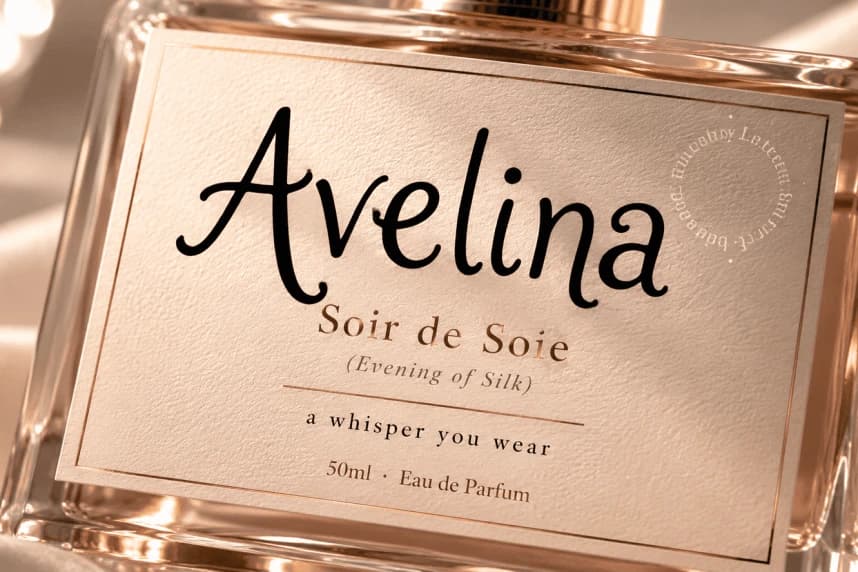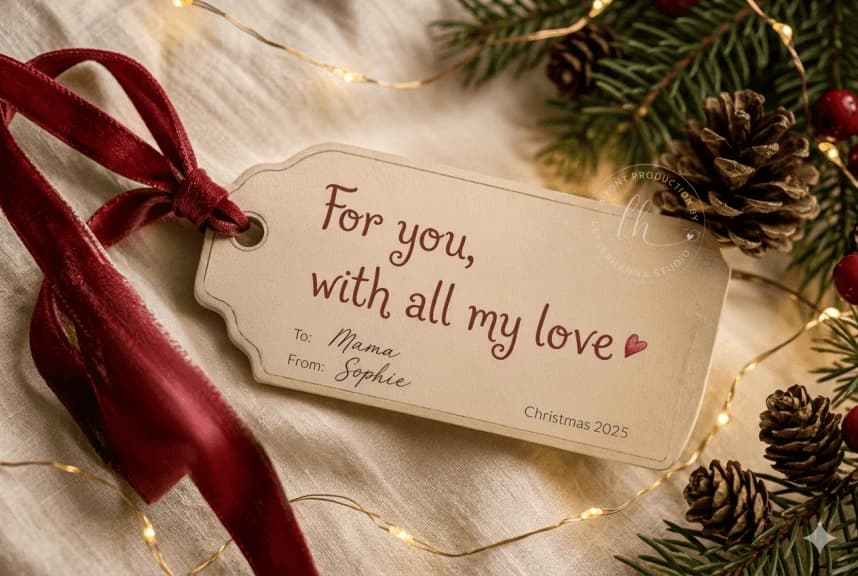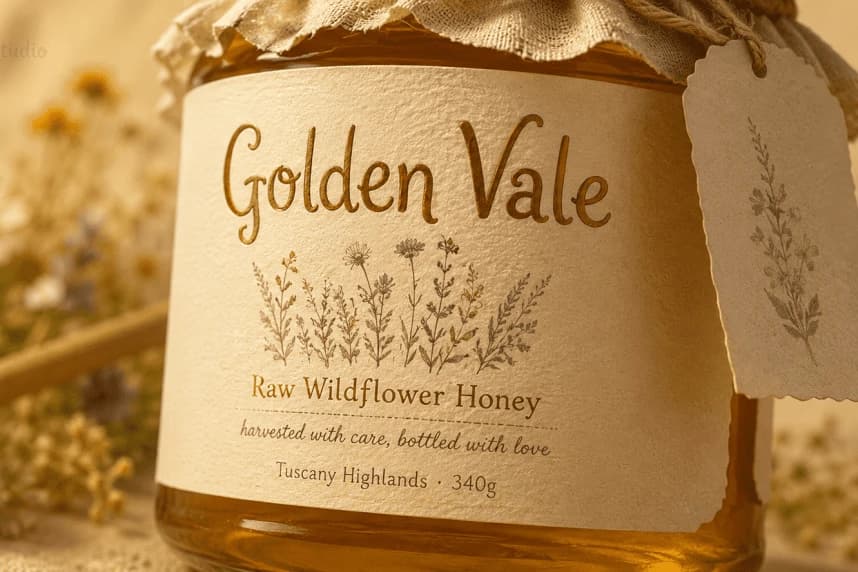
Junelys Ridge Font — kağıt üzerinde mürekkep gibi hareket eden, bir imza gibi kıvrılan ve her eğrinin zarafeti fısıldayan bir yazı tipidir; akıcı çizgileri, zarif spiral kıvrımları ve mükemmel dengeli harf biçimleriyle.
Junelys Ridge Font — kağıda mürekkep gibi hareket eden, imza gibi kıvrılan ve her eğrinde zarafeti fısıldayan bir script fontu. Akıcı hatlarıyla, zarif spiral süslemeleriyle ve mükemmel dengelenmiş harf biçimleriyle